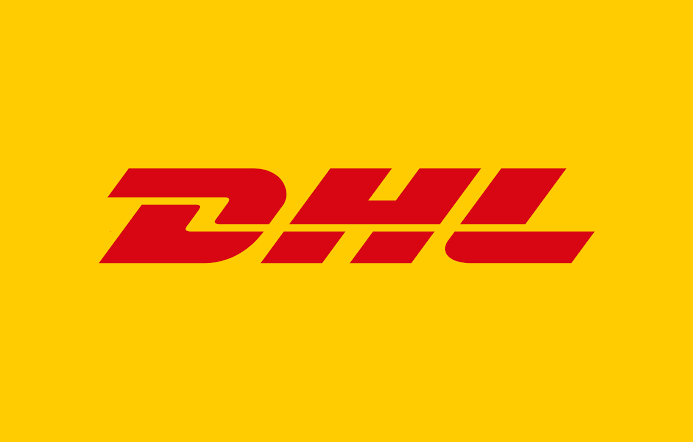
Arkadaşlar merhaba, tipografi dersi için bir markanın logosundan font yaratacağız da ancak markanın fontunun internette olmaması gerekiyor. what the fonttan arattım fakat bulamadım. acaba DHL'nin fontu var mı? benim için çok önemli. bir de sizin önerebileceğiniz marka varsa iyi olur teşekkürler
yakin ve benzer fontlar var ama
biri dafont da
It's not available as a font, it's just a logo made in 1968. I've worked for DHL for 11 years and I've never seen it as a font.